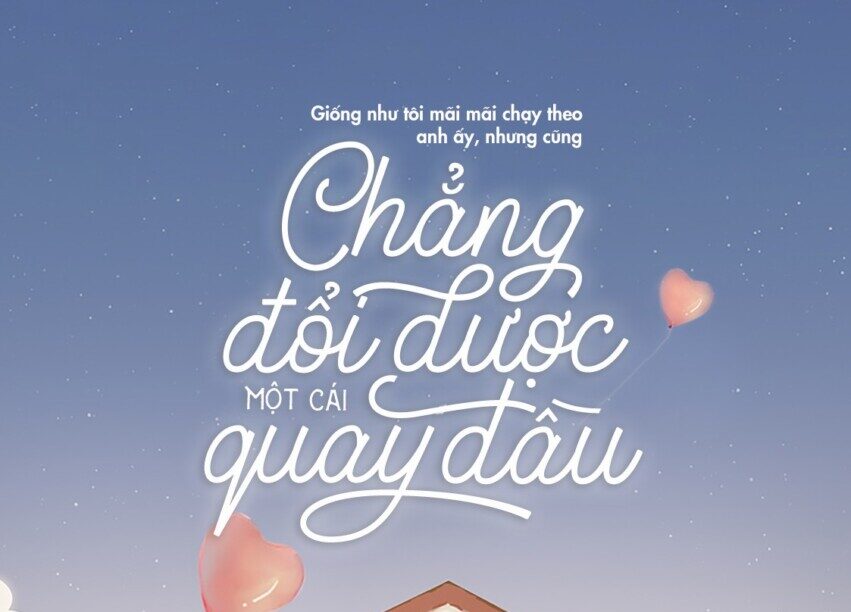
Khám Phá Vẻ Đẹp Sang Trọng Của Font Việt hóa MTD Geraldyne Cho Thiết Kế Tuyệt Vời
Nhu cầu tìm kiếm những bộ Font Chữ đẹp, độc đáo và chuyên nghiệp ngày càng trở nên quan trọng, đặc biệt đối với giới thiết kế, học sinh, sinh viên chuẩn bị cho các ấn phẩm quan trọng như kỷ yếu tốt nghiệp hay thiệp mời sự kiện. Trong số vô vàn lựa chọn, cái tên Font Việt hóa MTD Geraldyne đã nhanh chóng trở thành một hiện tượng, thu hút sự chú ý nhờ vẻ ngoài lãng mạn, thanh lịch và khả năng tương thích hoàn hảo với tiếng Việt. Đây không chỉ là một font chữ script thông thường mà còn là giải pháp typography tối ưu giúp nâng tầm mọi dự án đồ họa của bạn.
Font Việt hóa MTD Geraldyne: Điểm Nhấn Hoàn Hảo Cho Mọi Dự Án
MTD Geraldyne thuộc nhóm font script (chữ viết tay), nổi bật với các đường nét uốn lượn mềm mại, uyển chuyển, mang lại cảm giác cổ điển nhưng không kém phần hiện đại và sang trọng. Sự kết hợp giữa nét thanh và nét đậm được xử lý tinh tế tạo nên độ tương phản vừa phải, giúp font chữ không chỉ đẹp mắt mà còn dễ đọc, ngay cả trong các tiêu đề lớn hay các đoạn văn bản ngắn. Font này đặc biệt phù hợp cho các thiết kế cần sự nữ tính, lãng mạn hoặc yêu cầu tính trang trọng cao, là lựa chọn hàng đầu cho các ấn phẩm liên quan đến mùa tốt nghiệp hoặc thiệp mời cá nhân hóa.
Đặc Điểm Nổi Bật Của Bộ Font
Điều khiến MTD Geraldyne trở nên khác biệt chính là sự phong phú trong bộ ký tự thay thế (alternates) và các nét trang trí (swashes). Các nhà thiết kế có thể dễ dàng tạo ra những logo, thiệp mời cá nhân hóa độc đáo mà không cần phải can thiệp quá nhiều vào phần mềm đồ họa phức tạp. Bộ font này thường đi kèm nhiều style khác nhau, từ regular đến bold, cho phép người dùng linh hoạt lựa chọn tùy theo mục đích sử dụng. Ví dụ, việc áp dụng font này vào bìa kỷ yếu cuối cấp 3 sẽ tạo nên một ấn phẩm đáng nhớ và đầy cảm xúc, thể hiện sự chuyên nghiệp và gu thẩm mỹ tinh tế.
Tính năng Việt hóa đóng vai trò cốt lõi trong thành công của Font Việt hóa MTD Geraldyne. Trong nhiều font chữ nước ngoài đẹp, vấn đề thường gặp là lỗi hiển thị dấu tiếng Việt, khiến người dùng phải mất công chỉnh sửa hoặc bỏ qua, gây ảnh hưởng đến chất lượng dự án. Với phiên bản Việt hóa, mọi ký tự đặc trưng của tiếng Việt như ‘ă, â, đ, ê, ô, ơ, ư’ đều được thiết kế lại một cách tỉ mỉ, đảm bảo tính thẩm mỹ đồng nhất và độ chính xác tuyệt đối. Điều này giúp các học sinh, sinh viên khi làm bài tiểu luận hoặc thiết kế đồ án tốt nghiệp có thể tự tin sử dụng font mà không lo ngại về lỗi font hay thiếu ký tự, tiết kiệm thời gian đáng kể trong quá trình hoàn thiện bài tập và dự án.
Ứng Dụng Sáng Tạo Của MTD Geraldyne Trong Học Đường và Đồ Họa
Đối với môi trường học đường, đặc biệt là giai đoạn chuẩn bị cho lễ tốt nghiệp và các kỳ thi quan trọng, MTD Geraldyne là lựa chọn lý tưởng. Nó được sử dụng rộng rãi để thiết kế thiệp mời dự lễ, in trên giấy khen, bằng tốt nghiệp giả lập, hoặc tạo các header ấn tượng cho báo tường, tạp chí lớp. Độ thanh thoát của font mang lại cảm giác chuyên nghiệp và uy tín, rất phù hợp với các ấn phẩm mang tính chất kỷ niệm và trang trọng. Các khóa học về typography hoặc thiết kế cơ bản cho học sinh trung học cũng thường lấy các font script đẹp như MTD Geraldyne làm ví dụ minh họa về tính biểu cảm và nghệ thuật của chữ viết, giúp các em học sinh làm quen với các tiêu chuẩn thiết kế hiện đại.
Các nhà thiết kế chuyên nghiệp cũng đánh giá cao MTD Geraldyne vì tính linh hoạt của nó. Ngoài thiệp mời cưới hoặc branding cao cấp, font này còn rất hiệu quả khi dùng trong các ấn phẩm kỹ thuật số, banner quảng cáo sự kiện hoặc chữ ký cá nhân hóa. Với sự hỗ trợ của các phần mềm như Adobe Illustrator hay Photoshop, việc tùy chỉnh các nét uốn lượn và kết hợp màu sắc trở nên dễ dàng, giúp tối ưu hóa hiệu quả thị giác của sản phẩm cuối cùng. Font chữ này mang lại cảm giác thủ công, cá nhân hóa cao, điều mà các thương hiệu cao cấp và các dự án thiết kế nghệ thuật rất cần.
So Sánh Font MTD Geraldyne Với Các Font Script Khác
Khi so sánh với các font script phổ biến khác trên thị trường, MTD Geraldyne thường được khen ngợi về sự cân bằng giữa nghệ thuật và khả năng ứng dụng thực tế. Nhiều font viết tay khác quá cầu kỳ hoặc quá đơn giản, nhưng MTD Geraldyne duy trì được sự sang trọng mà vẫn đảm bảo tính dễ đọc. Khả năng Việt hóa chất lượng cao cũng là một lợi thế cạnh tranh lớn, giúp font này vượt trội hơn các đối thủ chỉ hỗ trợ bộ ký tự Latin cơ bản. Việc lựa chọn font chữ phù hợp là bước đầu tiên để đảm bảo dự án thiết kế, dù là bài thuyết trình của học sinh hay một chiến dịch quảng cáo lớn, đều đạt được hiệu quả truyền tải thông điệp tốt nhất. Đây là yếu tố then chốt cho mọi ấn phẩm.
Để tận dụng tối đa font chữ này, người dùng nên tìm hiểu kỹ về các tính năng OpenType nâng cao mà nó cung cấp. Đôi khi, một chút thay đổi ở nét đầu hoặc nét cuối của chữ cái cũng có thể thay đổi hoàn toàn phong cách của tiêu đề. Điều này đặc biệt quan trọng khi thiết kế logo hoặc các ký tự chữ cái lớn, nơi sự tỉ mỉ trong từng chi tiết typography đóng vai trò quyết định đến nhận diện thương hiệu.
Một mẹo nhỏ cho những ai đang thiết kế các ấn phẩm thi cử hoặc học thuật là nên kết hợp MTD Geraldyne (dùng cho tiêu đề, tên sự kiện) với một font serif hoặc sans-serif sạch sẽ (dùng cho nội dung chính) để tối ưu hóa khả năng đọc. Sự tương phản giữa nét lãng mạn của MTD Geraldyne và nét hiện đại, rõ ràng của các font cơ bản tạo nên hiệu ứng thị giác mạnh mẽ, giúp bài thiết kế trở nên chuyên nghiệp và thu hút hơn mà không làm giảm đi tính học thuật của nội dung.
Tóm lại, Font Việt hóa MTD Geraldyne là một tài sản vô giá trong bộ sưu tập của bất kỳ nhà thiết kế, học sinh, hay giáo viên nào. Với vẻ đẹp lãng mạn, các đường nét tinh tế và đặc biệt là khả năng Việt hóa hoàn hảo, nó không chỉ đáp ứng yêu cầu thẩm mỹ cao mà còn giải quyết triệt để các vấn đề kỹ thuật liên quan đến typography tiếng Việt. Việc đầu tư thời gian tìm hiểu và áp dụng bộ Font Chữ này chắc chắn sẽ mang lại giá trị vượt trội cho các dự án sắp tới của bạn, từ các ấn phẩm cá nhân đến các tài liệu chính thức của trường học hoặc các kỳ thi quan trọng, giúp thông điệp của bạn được truyền tải một cách trọn vẹn và đẳng cấp nhất.